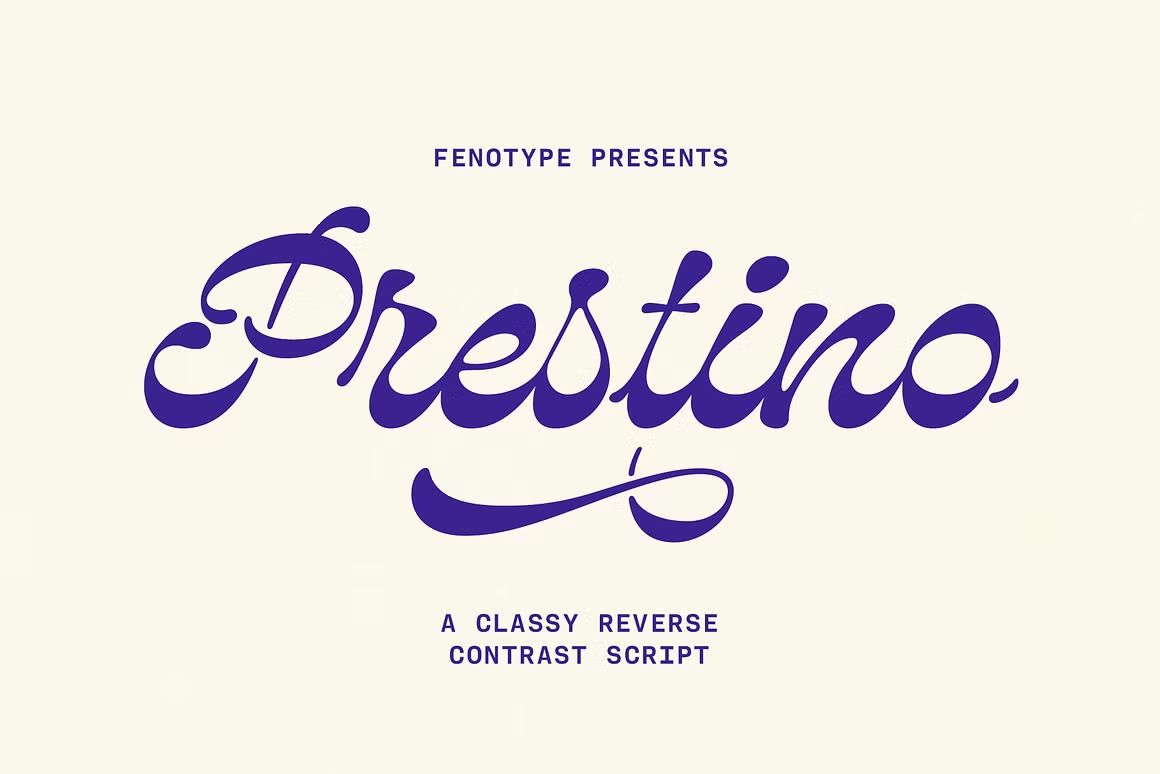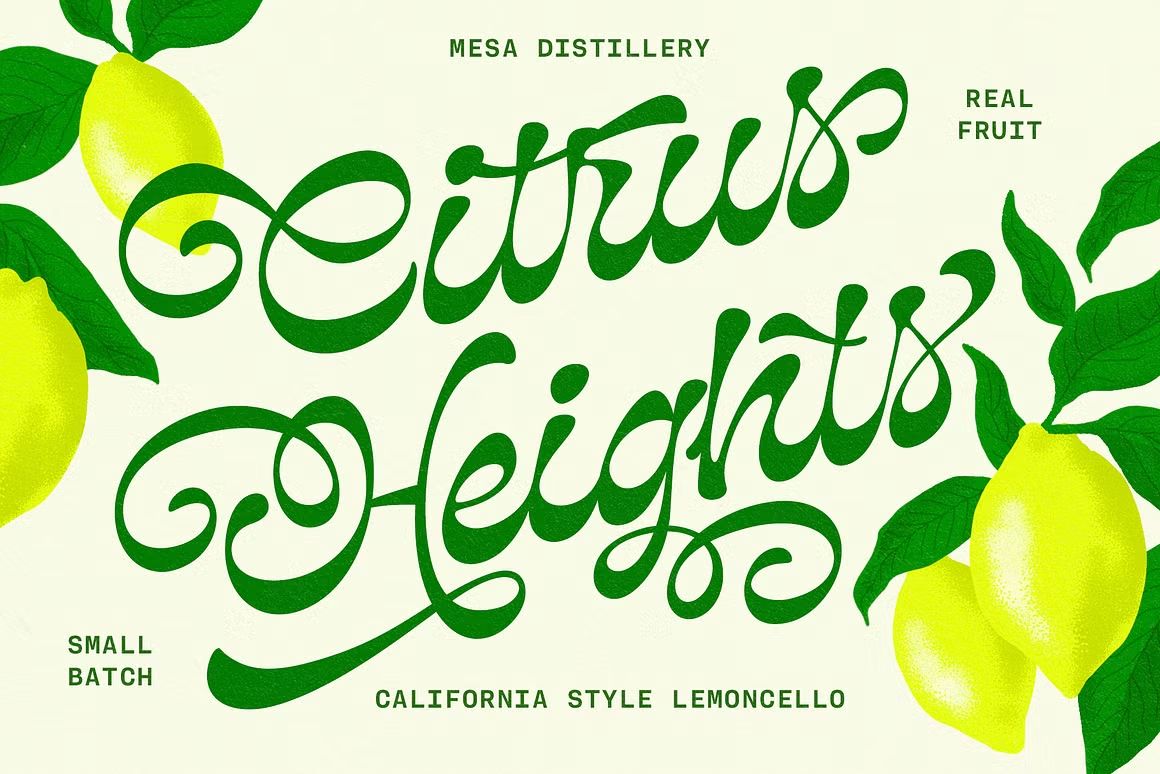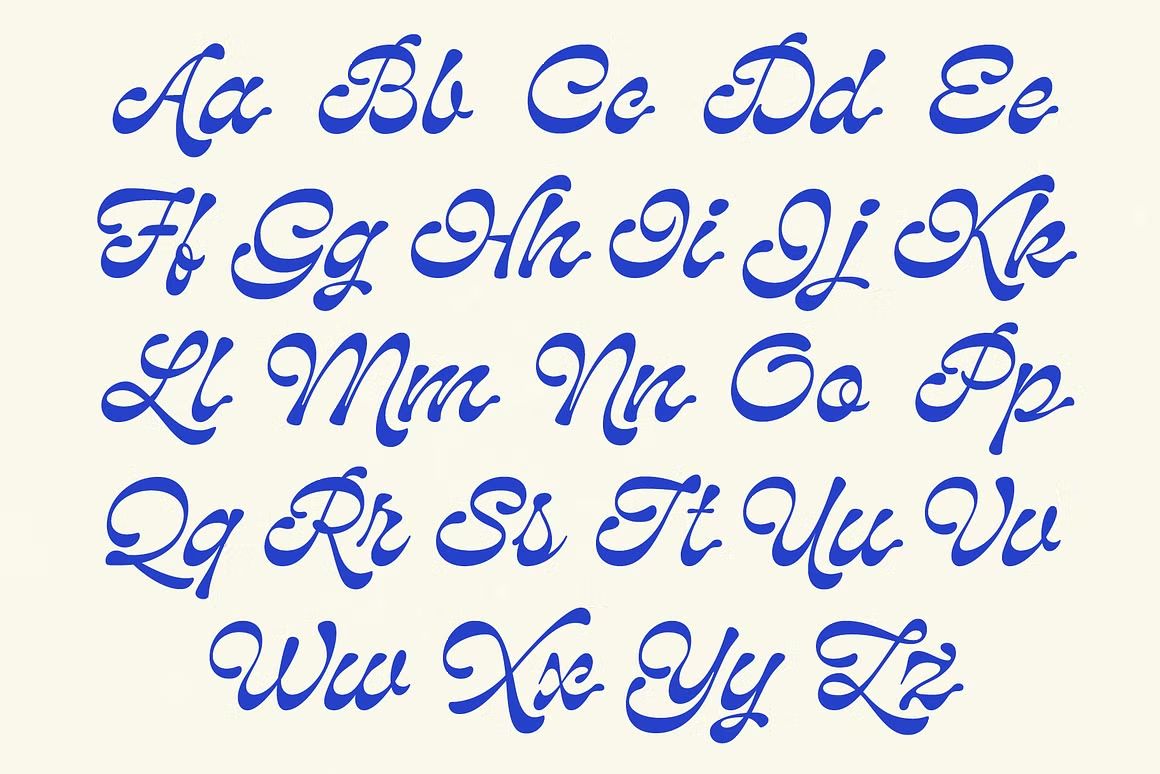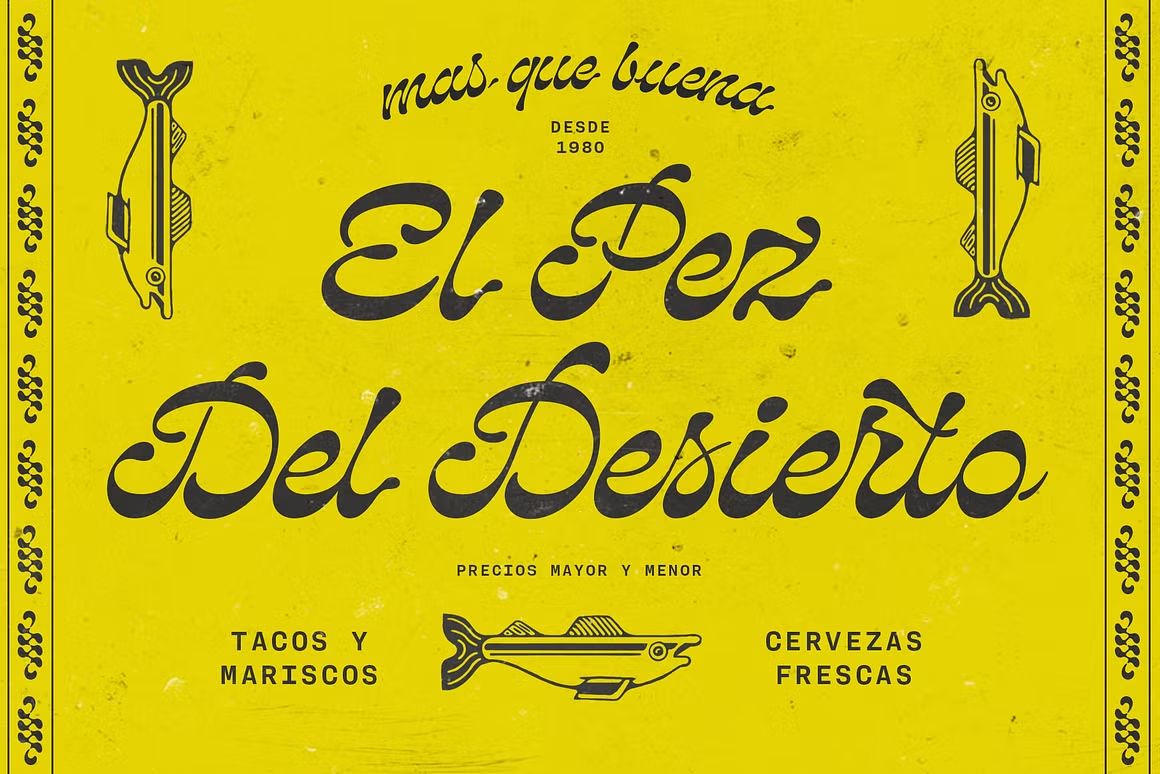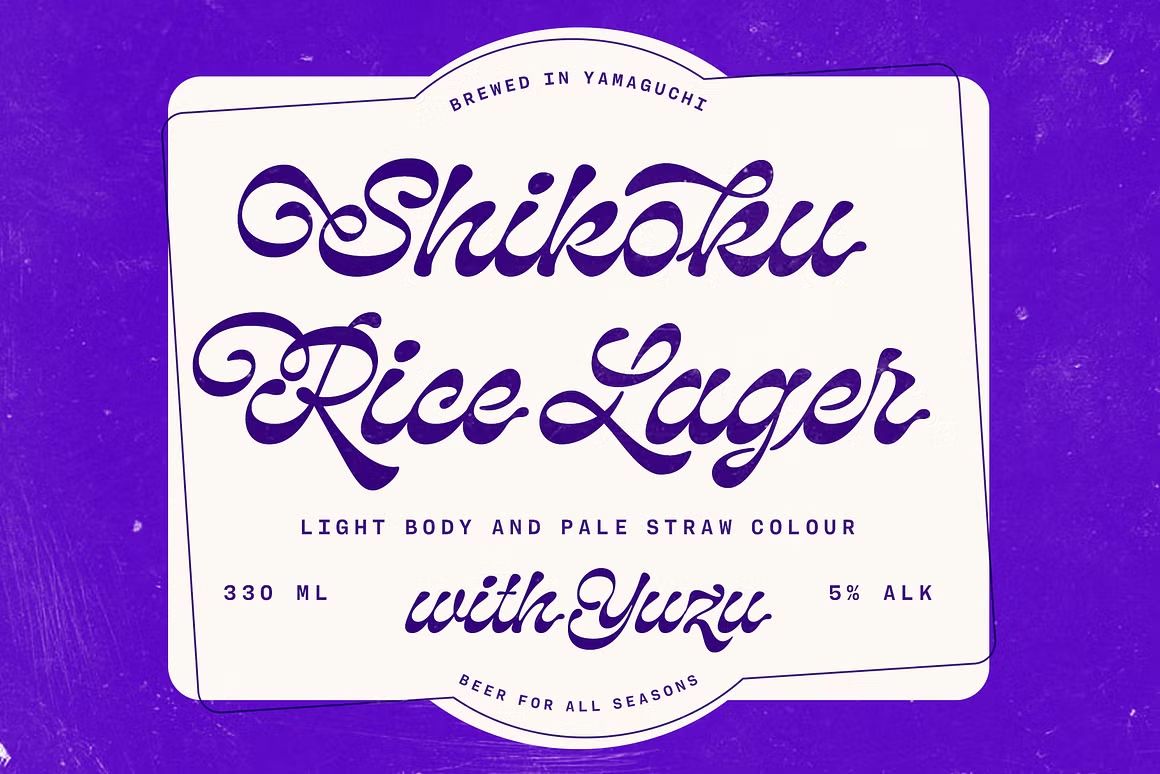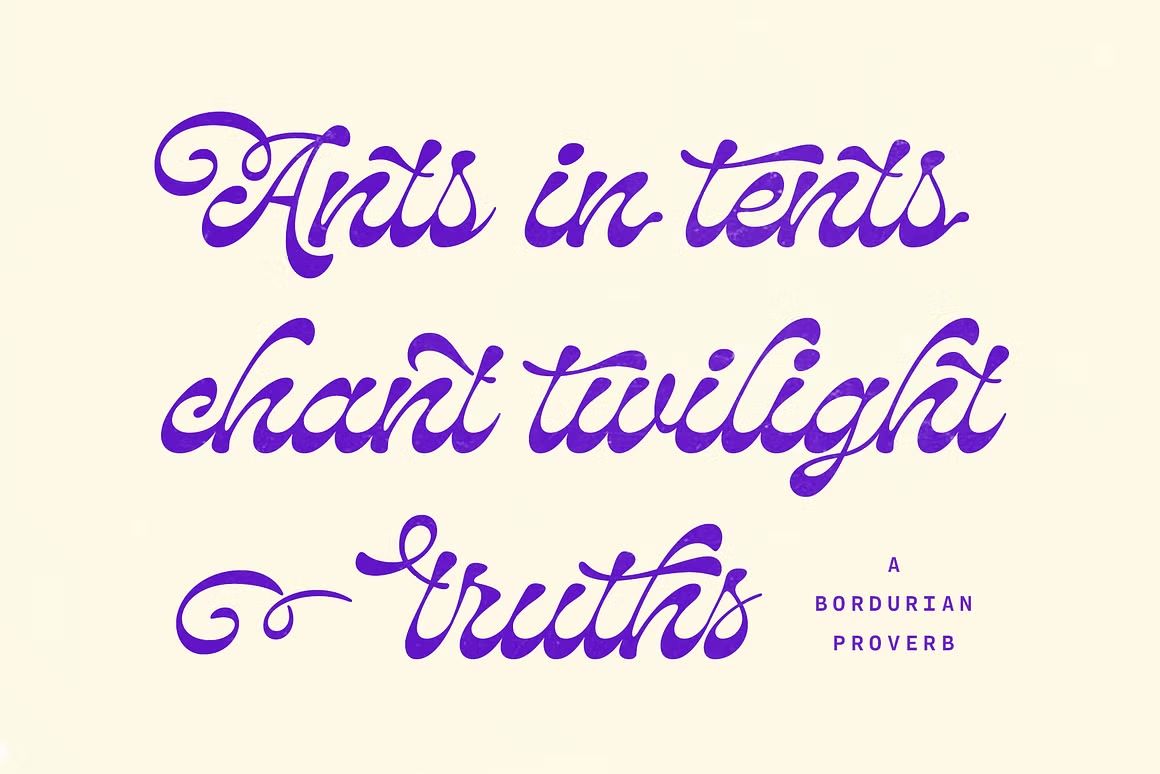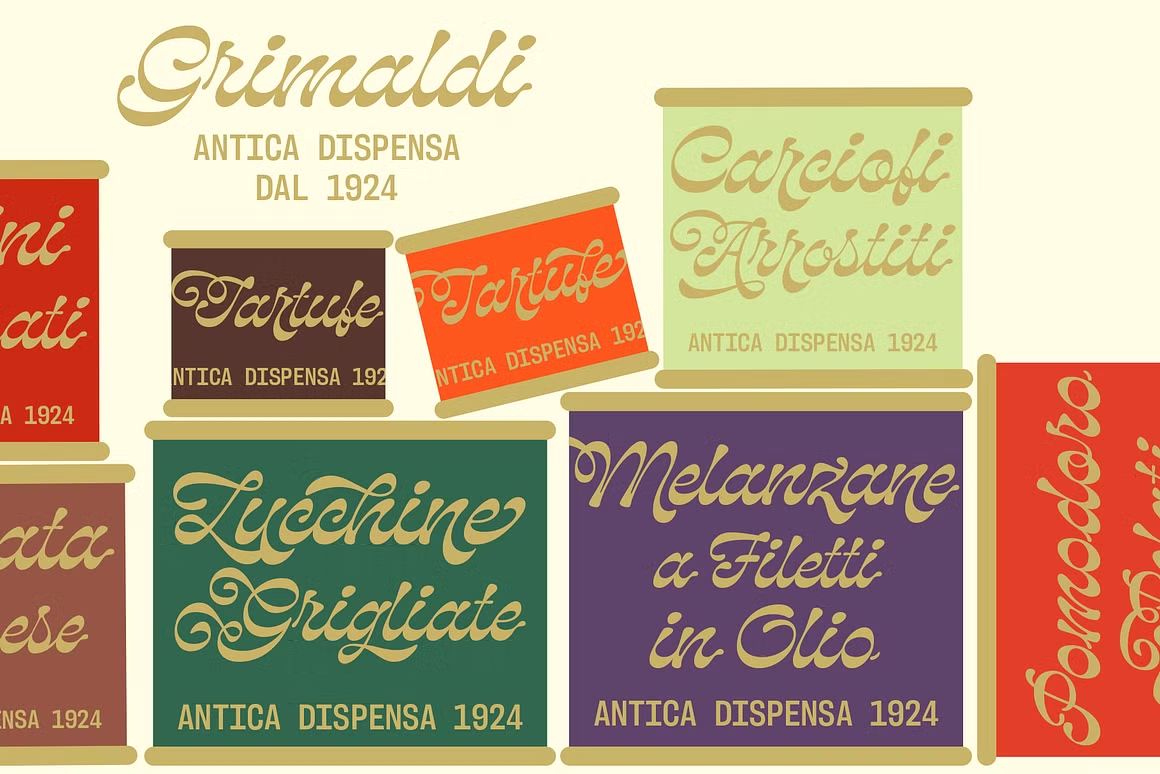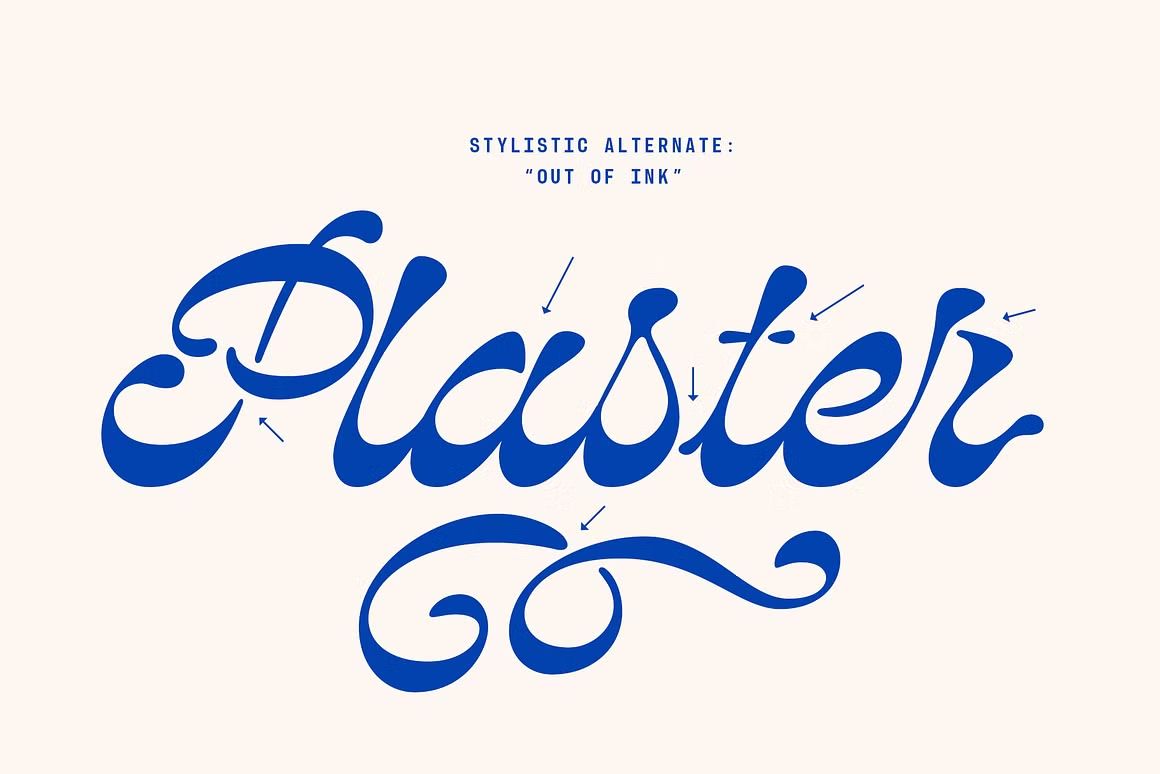
Prestino – Classy Script
Prestino adalah font script bergaya classy dengan garis halus dan elegan, sempurna untuk desain undangan, logo, branding, dan proyek kreatif yang menginginkan sentuhan mewah dan feminin.
Prestino adalah font script yang memadukan keanggunan dan kehalusan dalam setiap lekuk hurufnya. Dengan gaya tulisan tangan yang mewah dan profesional, Prestino sangat cocok untuk digunakan pada undangan pernikahan, logo brand fashion, kemasan produk, dan berbagai proyek kreatif yang membutuhkan sentuhan feminin dan eksklusif.
Fitur unggulan:
• Gaya script classy yang elegan dan mengalir indah
• Cocok untuk undangan, logo, branding, dan desain bernuansa mewah
• Termasuk huruf besar, huruf kecil, angka, dan simbol
• Ideal untuk proyek cetak dan digital dengan sentuhan feminin dan premium